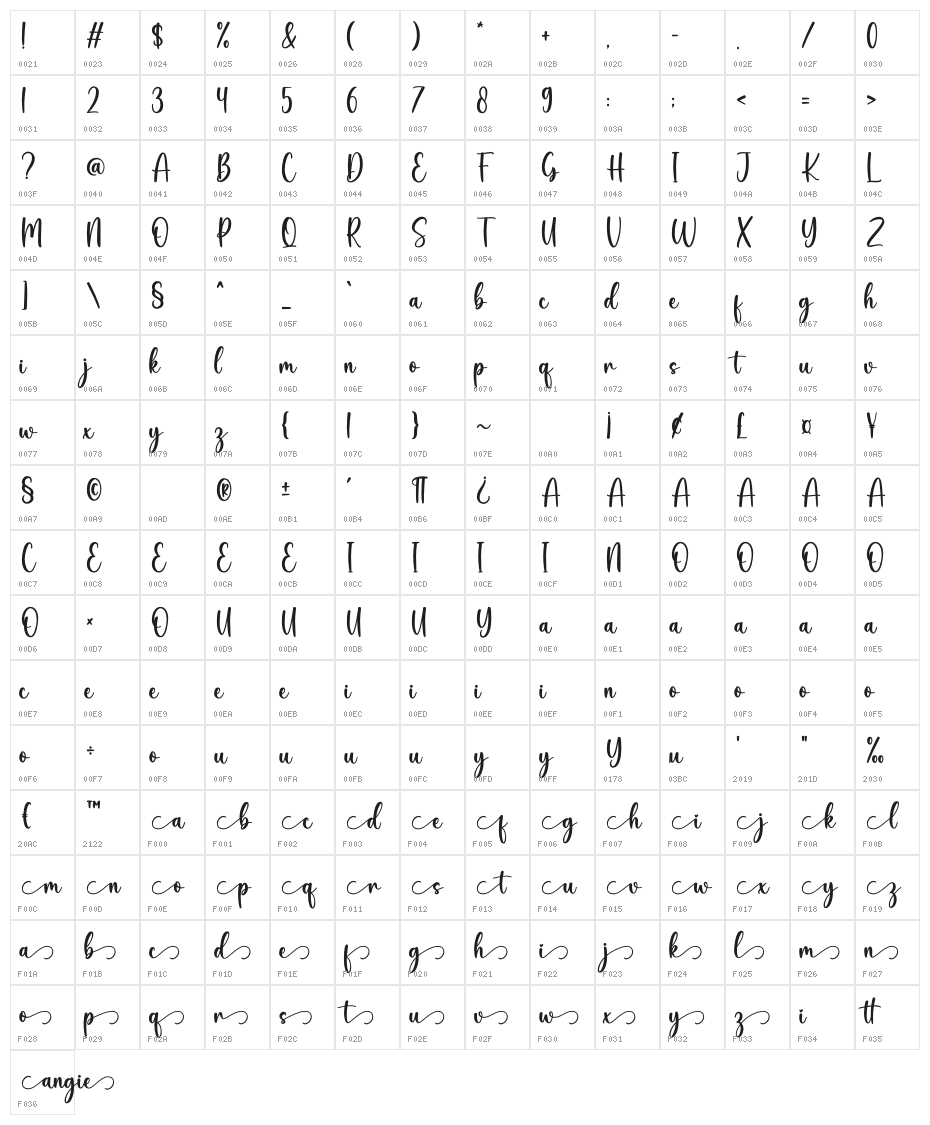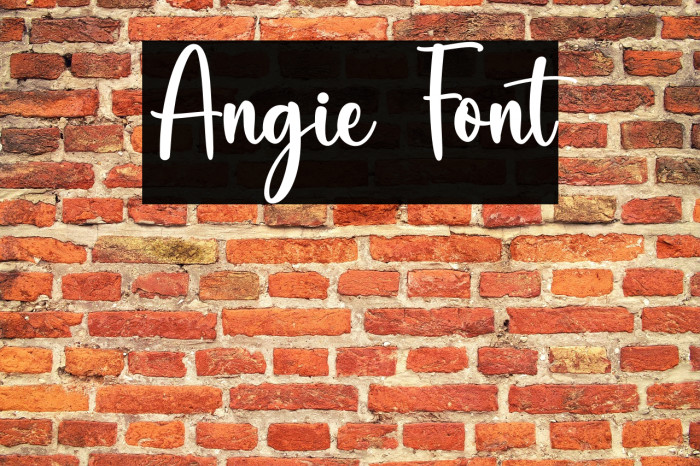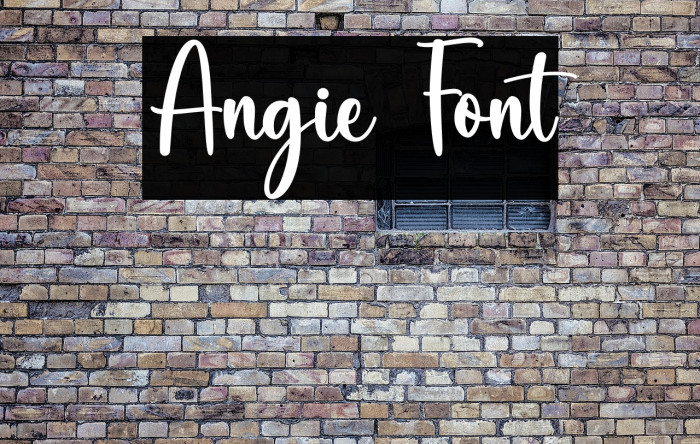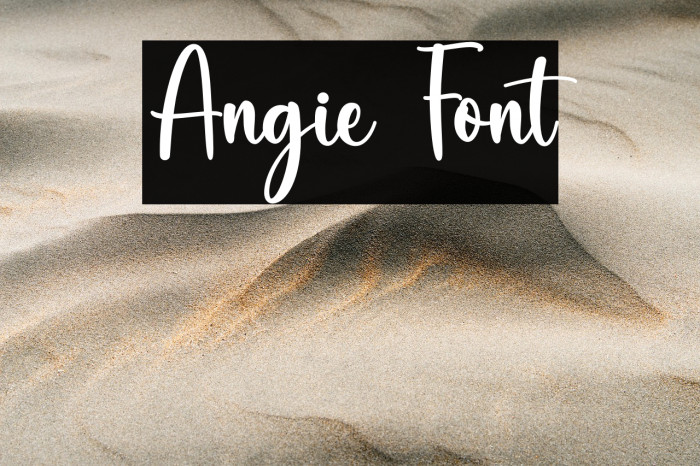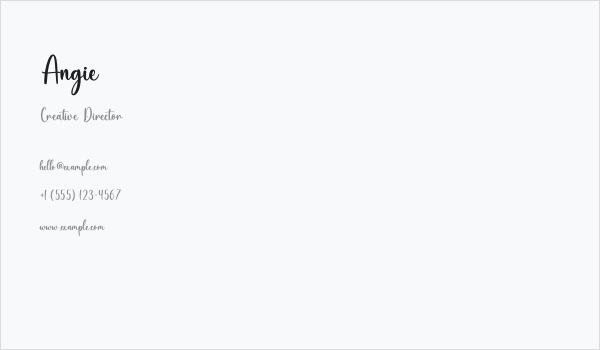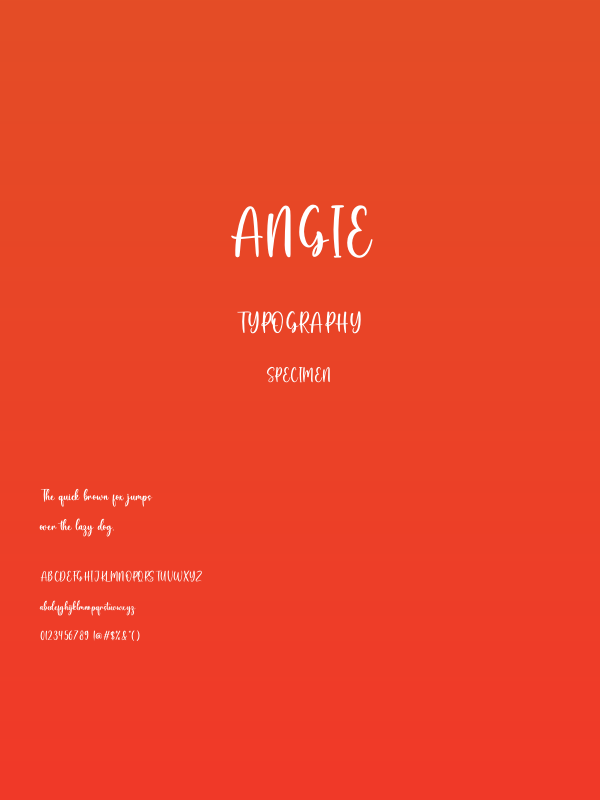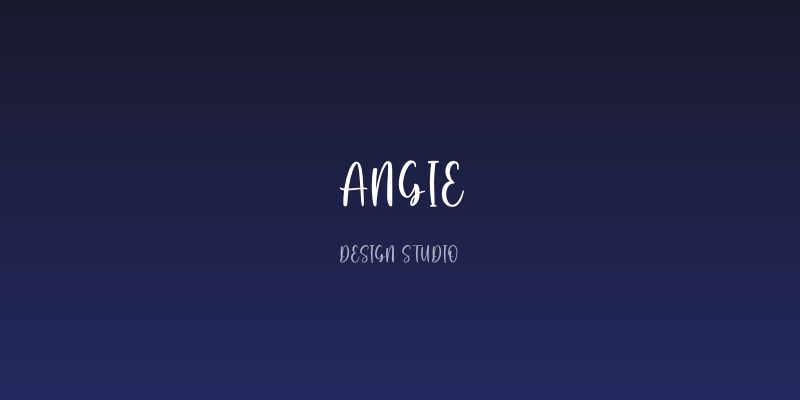
Angie Font
ANGIE MAIUSCOLE
ANGIE MINUSCOLO
ANGIE ALTRI CARATTERI
| Nome | Angie |
| Stile generale | Playful, Whimsical |
| Caso d'uso | Headlines, Logos, Creative projects |
| Progetti proposti | Ideal for greeting cards, invitations, personal branding, and creative social media graphics. |